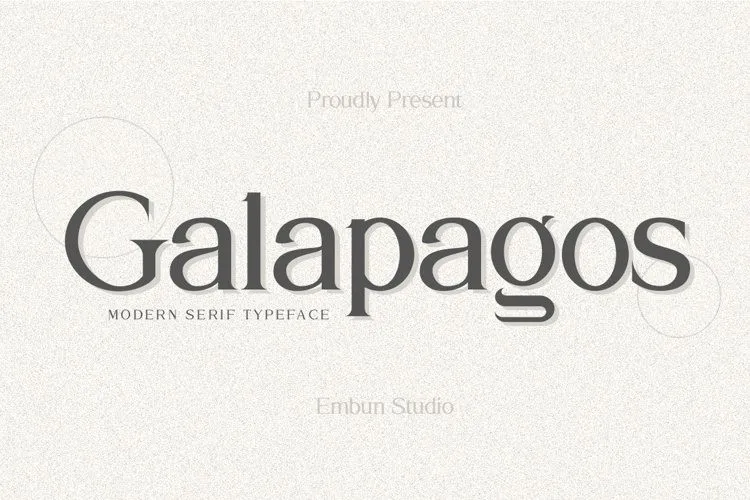
Galapagos Serif Font – Download Grátis
A Galapagos Serif Font é uma elegante escolha para projetos que exigem sofisticação e luxo. Sua característica clara dos traços acentuados cria um ar de refinamento e serenidade perfeita para textos importantes, como títulos ou texto em magazines. Embun Studio criou essa font exclusivamente para projetos de alta costura, mas seu charme universal irá agregar valor a qualquer projeto que busque uma conotação luxuosa e elegante. Seja para capas de revistas, postagens em redes sociais ou qualquer outro tipo de design visual desejando transmitir um toque sofisticado, esta font é perfeita. Ao usar Galapagos Serif Font em seus projetos, você encontrará uma beleza única, luxo e serenidade que o torna definitivamente seu escolha ideal para trabalhos de alta qualidade.